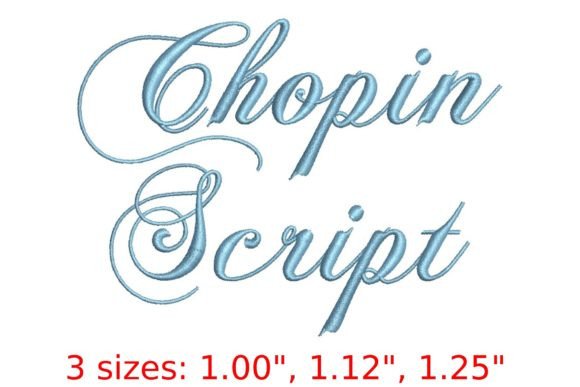
Chopin Script Embroidery Font
Шрифт Chopin Script Embroidery Font — це елегантне, ручно створене рішення для цифрового вишивального дизайну у форматі PES, яке імітує класичний каліграфічний почерк Фредеріка Шопена: плавні згини, витончені заспіли, різноманітна товщина ліній та природна асиметрія, що надає кожному напису живості й особистого шарму. Цей шрифт не просто відтворює літери — він передає настрій, грацію та музикальність, роблячи його ідеальним вибором для вишивки на святкових серветках, подарункових скатертин, вишитих портретів, іменних бейджів чи ексклюзивних текстильних етикеток.
Якість збірки та технічні деталі
Шрифт розроблений спеціально для вишивальних машин з підтримкою формату PES (Brother, Baby Lock тощо) і включає повний набір літер верхнього та нижнього регістрів, цифр, основних знаків пунктуації та спецсимволів. Кожен символ оптимізований за щільністю стібків (2–3,5 мм/см), має стабільну керовану нитку, мінімальну кількість обривів та коректну обробку перехресних ліній. Всі контури мають точну векторну основу з подальшим конвертуванням у стібкові шаблони за допомогою професійного ПЗ (напр., Wilcom E4/E6 або Pulse). Завантажується у вигляді ZIP-архіву з окремими PES-файлами для кожної літери, а також готовим комплектом для автоматичної генерації тексту (з підтримкою kerning’у та масштабування 8–40 мм).
Перед вишивкою завжди проводьте тестовий запуск на тканині-аналогі (з тим самим типом підкладки та нитками), оскільки Chopin Script має тонкі лінії — для забезпечення чіткості рекомендуємо використовувати стабілізатор з середньою жорсткістю (напр., Sulky Tender Touch або Pellon 906F) і нитки Rayon або преміум-поліестер з товщиною 40/2.
Як це порівнюється з конкурентами
На відміну від загальних безкоштовних PES-скриптів (напр., 'Lavanderia' або 'Sweet Pea'), Chopin Script пропонує значно вищу ступінь каліграфічної автентичності, стабільнішу стібкову структуру та професійну оптимізацію під реальні машини. У порівнянні з преміальними альтернативами (напр., 'Zephyr Script' від Urban Threads або 'Aurora Script' від Embroidery Library), Chopin виділяється більш вираженою музичною ритмікою ліній, ширшим діапазоном масштабування без втрати деталізації та вбудованою підтримкою керування міжлітерними відстанями (kerning) — що робить його більш універсальним для складних проектів з довгими фразами.